Font Elegant Việt hóa là nhóm các phông chữ mang phong cách sang trọng, thanh lịch và tinh tế, thường được sử dụng để nâng tầm giá trị cho các bản thiết kế thương hiệu cao cấp. Khác với các dòng phông chữ phổ thông, font Elegant chú trọng vào tỉ lệ vàng, những đường nét thanh thoát và độ tương phản nét thanh đậm sắc sảo. Doozypack.vn chia sẻ link tải font Elegant Việt hóa trọn bộ, giúp bạn sở hữu những bộ font Elegant tiếng Việt chỉn chu nhất để hiện thực hóa các ý tưởng thiết kế bao bì, logo và ấn phẩm truyền thông Luxury.
Đặc điểm nhận diện của các dòng font Elegant Việt hóa
Một phông chữ được xếp vào nhóm “Elegant” (thanh lịch) không chỉ ở vẻ bề ngoài mà còn ở cảm xúc mà nó truyền tải đến khách hàng.
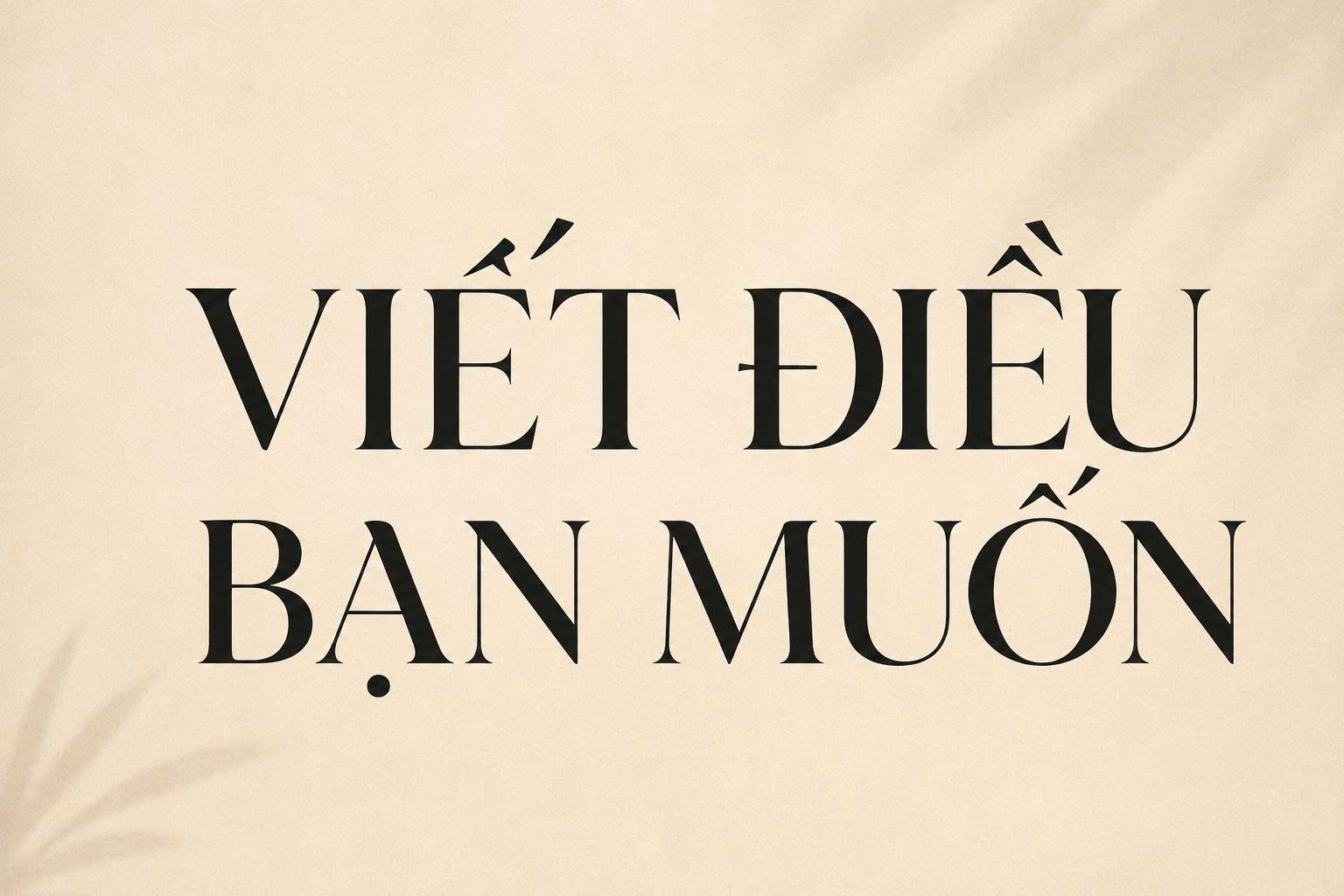
Sự kết hợp giữa nét thanh và nét đậm tinh tế
Đặc trưng lớn nhất của font Elegant Việt hóa là độ tương phản nét chữ. Bạn sẽ thường thấy các nét dọc chắc chắn kết hợp cùng các nét ngang hoặc nét nối thanh mảnh như sợi tóc (hairline). Sự đối lập này tạo nên nhịp điệu Typography vô cùng lôi cuốn, mang lại diện mạo đắt tiền cho mọi tiêu đề bản thiết kế.
Cấu trúc chữ Serif hiện đại hoặc Sans-serif nhân văn
Phần lớn các bộ font sang trọng thuộc dòng Serif (có chân) hiện đại với phần chân chữ phẳng và sắc nét. Tuy nhiên, cũng có nhiều dòng Sans-serif (không chân) được thiết kế theo phong cách Humanist với các đường cong mở rộng, tạo cảm giác minh bạch nhưng vẫn vô cùng quý phái. Khi được Việt hóa tại Doozypack.vn, hệ thống dấu thanh được xử lý mảnh mai để không phá vỡ cấu trúc tổng thể thanh lịch của phông chữ.
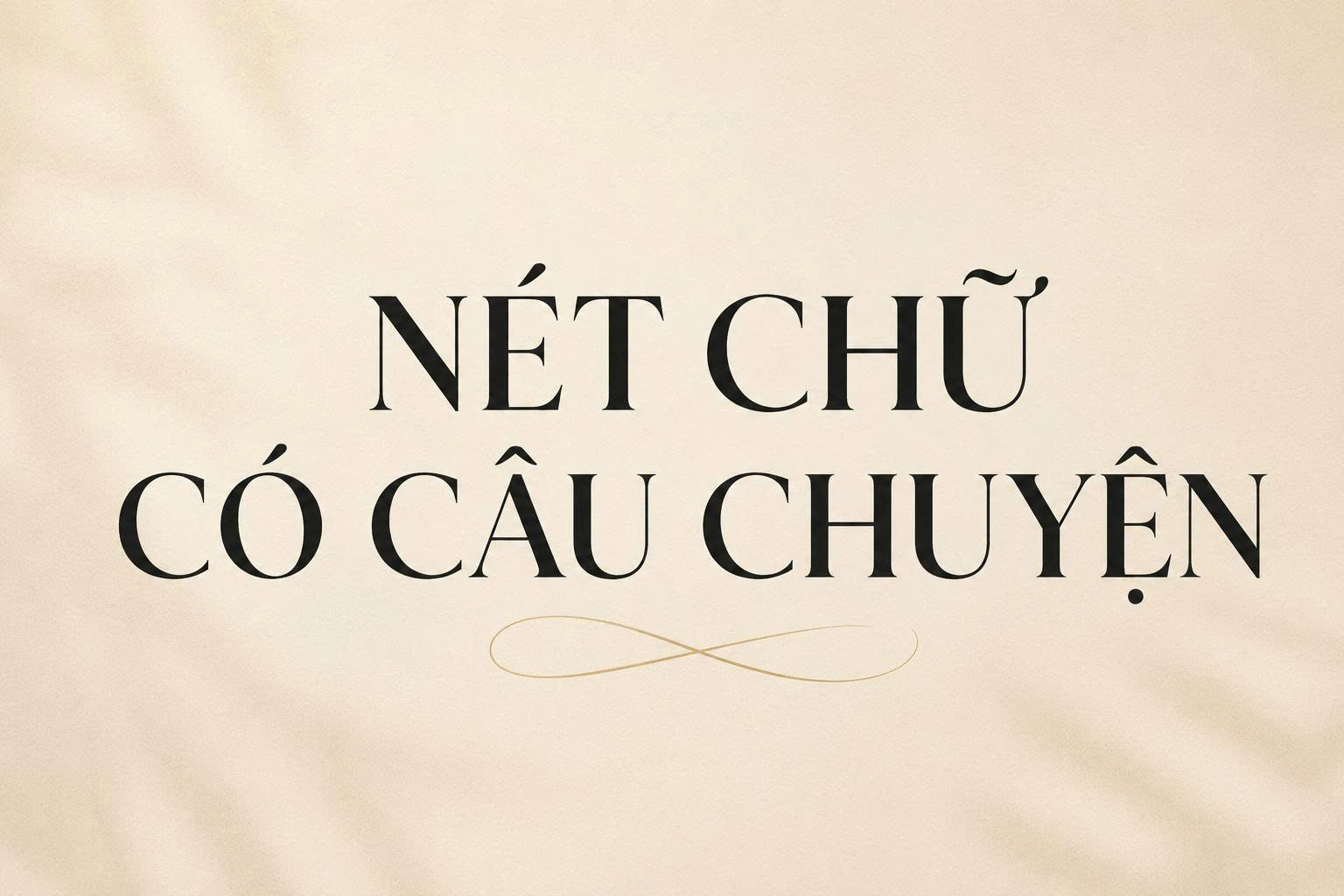
Tại sao thiết kế bao bì Luxury cần font chữ Elegant tiếng Việt?
Trong ngành sản xuất bao bì tại Doozypack.vn, việc lựa chọn đúng font chữ quyết định đến 70% cảm nhận về giá trị sản phẩm:
- Giải quyết triệt để lỗi font: Bản Việt hóa chuẩn giúp bạn thiết kế các slogan như “Tinh hoa thảo mộc” hay “Nâng tầm đẳng cấp” một cách trọn vẹn, không bị lỗi nhảy font ở các ký tự đặc thù.
- Xây dựng niềm tin với khách hàng: Font chữ Elegant tạo cảm giác về một thương hiệu lâu đời, uy tín và chuyên nghiệp, giúp khách hàng sẵn sàng chi trả mức giá cao hơn cho sản phẩm.
- Đồng bộ nhận diện: Giúp bộ nhận diện thương hiệu từ Card visit, Website đến hộp giấy sản phẩm có chung một ngôn ngữ thiết kế sang trọng.
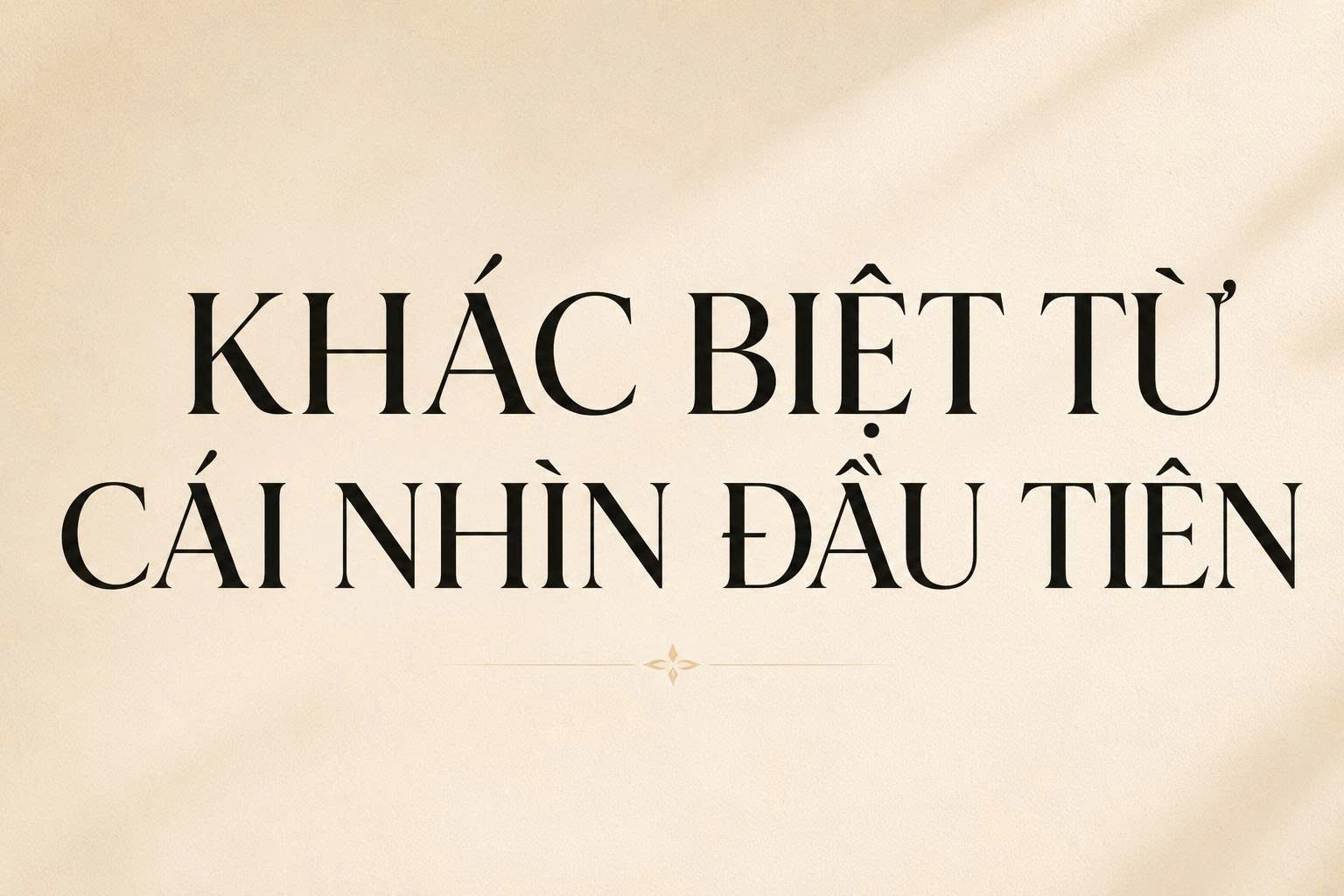
| Nhóm Font | Phong cách thiết kế | Ứng dụng đề xuất tại Doozypack.vn |
| Serif Elegant | Cổ điển, Quý tộc | Thiết kế hộp rượu, nhãn nước hoa, bao bì mỹ phẩm cao cấp. |
| Sans-serif Elegant | Hiện đại, Tối giản | Thiết kế Logo startup công nghệ, túi giấy thời trang Urban. |
| Script Elegant | Nghệ thuật, Bay bổng | Dùng cho thiệp mời VIP, thư tri ân khách hàng trong hộp quà. |
Tư vấn từ xưởng in: Đối với các thiết kế in ấn trên giấy Ivory hoặc Couche cán màng mờ, bạn nên ưu tiên các dòng Serif có độ tương phản cao. Nếu in trên giấy Kraft thô mộc, hãy chọn các font Elegant có nét hơi dày một chút để đảm bảo mực in không bị nhòe làm mất form chữ.
03 Ứng dụng của font Elegant trong in ấn tại Doozypack.vn
Vẻ đẹp thanh lịch của nhóm font này mang lại hiệu quả thị giác đặc biệt trên các ấn phẩm thực tế:
- Hộp trang sức & Đồng hồ: Sử dụng font Elegant tiếng Việt kết hợp kỹ thuật ép kim mờ (Matte Gold) trên nền hộp đen tạo nên vẻ ngoài vô cùng đẳng cấp.
- Bao bì mỹ phẩm & Spa: Nét chữ thanh thoát của font Elegant gợi cảm giác sạch sẽ, thư giãn và chăm sóc tận tâm.
- Túi giấy doanh nghiệp: Tên công ty in bằng font Elegant Bold trên túi giấy Ivory giúp khẳng định gu thẩm mỹ tinh tế của thương hiệu đối với khách hàng.
03 Lưu ý kỹ thuật khi in ấn font nét mảnh sang trọng
Sản xuất bao bì sử dụng phông chữ nghệ thuật đòi hỏi designer cần lưu ý một số vấn đề kỹ thuật tại xưởng in chuyên nghiệp:
- Vấn đề Hairline khi ép kim: Nhiều font Elegant có nét cực mảnh. Khi làm khuôn ép kim (Hot Stamping), nếu nét quá nhỏ sẽ khó bám nhũ. Doozypack.vn khuyên bạn nên tăng nhẹ độ dày nét chữ (Stroke) khoảng 0.05pt – 0.1pt trước khi làm khuôn.